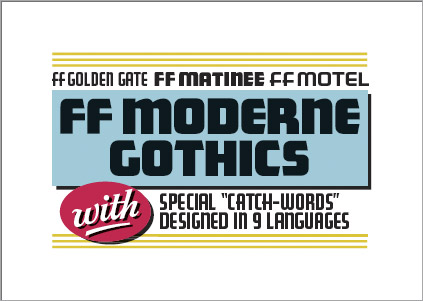
Sammelkarte: Moderne GothicsIm Juli 1997 erschien erstmals eine Schriftfamilie von Jim Parkinson bei
FontFont. Unter dem Sammelnamen »Moderne Gothics« fasste Parkinson
drei Headline-Schriften zusammen sowie einen Satz fertiger Wortmarken (in einen
Bei den drei Schriften FF Golden Gate™, FF Matinee™ und FF
Motel™, die im Paket FF Moderne Gothics zusammengefaßt sind,
handelt es sich um Schriften im Stil der 20er Jahre, allesamt Versalalphabete
mit Alternativbuchstaben. Solche Schriften waren bei Beschriftungen und im
Plakatbereich sehr weit verbreitet. Eine Besonderheit sind zwei
Zeichensätze mit »Fangwörtern« in verschiedenen Sprachen,
die sich in ungezählten Varianten mit den individuell gesetzten Begriffen
aus den Moderne Gothics kombinieren lassen.